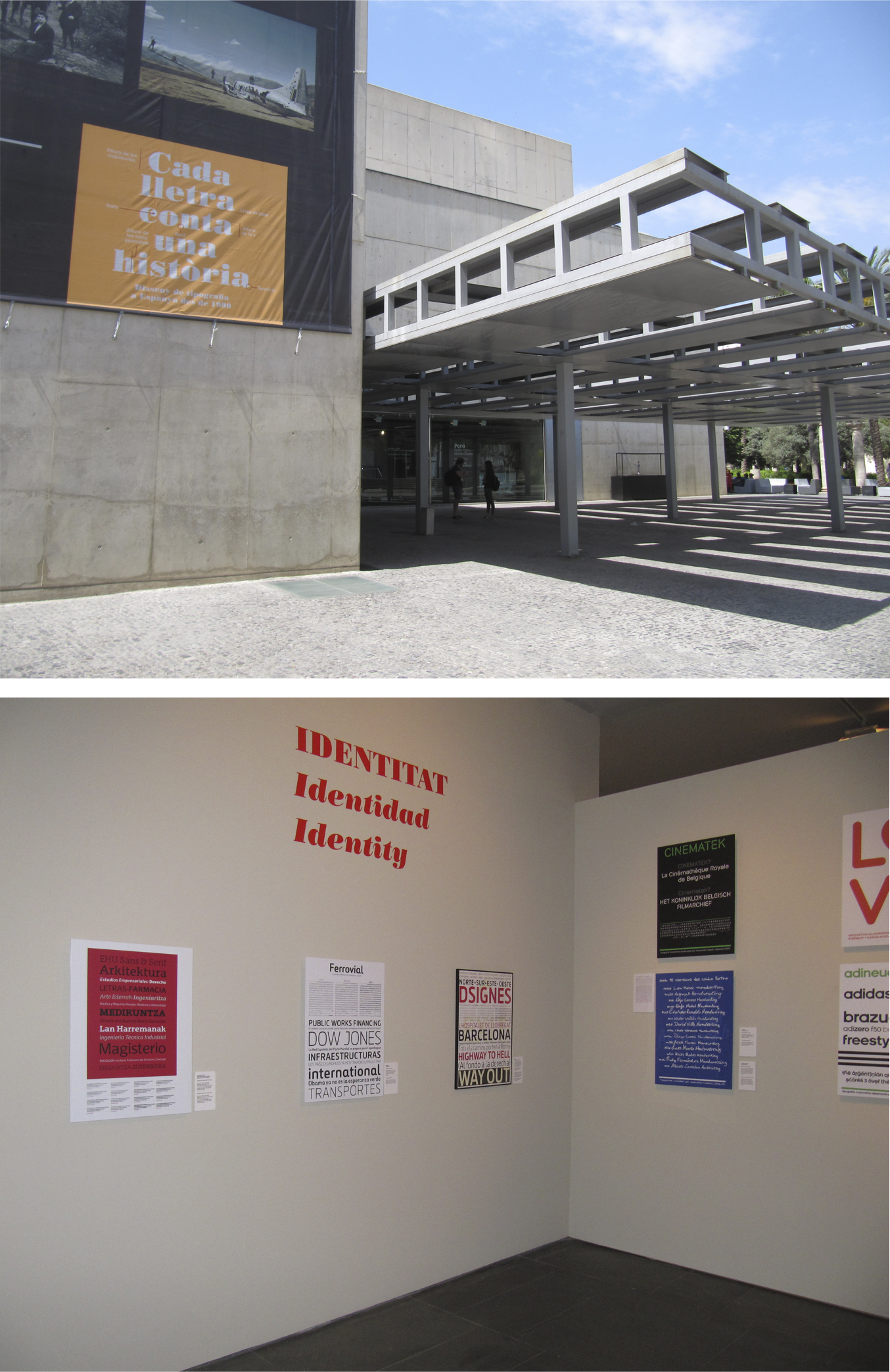
Exposición de caligrafía.
Kaligrafia Arantzazun: idazkera ederraren artea
Caligrafía en Arantzazu: el arte de la bellas escritura
El proyecto «Arantzazu Letraz gunea», fruto de la colaboración entre el Grupo de Investigación en Diseño Gráfico y Tipografía de la UPV/EHU «Letraz», y la Fundación Arantzazu Gaur, ha reunido en Arantzazu a trece de los más renombrados calígrafos del panorama internacional bajo el título Caligrafía en Arantzazu: el arte de la bella escritura. Esta exposición resulta excepcional puesto que se trata de la primera vez que se muestran al público textos en euskera caligrafiados por profesionales:
Ivan Castro
Ewan Clayton
Allan Daastrup
Jota Domínguez
Esther Gordo
Joluvian
Víctor Kams
Oriol Miró
Mr. Zé
Josemaría Passalacqua
Joan Quirós
Esperanza Serrano
Bego Viñuela
Estos calígrafos han manuscrito los poemas de Salbatore Mitxelena Arantzan-zu? (¿Tú en el espino?), Euria (La lluvia) y un fragmento de la canción popular Aldapeko sagarraren (Del manzano de la cuesta), recogidos en el libro Arantzazu: euskal-sinismenaren poema (Arantzazu: poema de fe vasca) de 1949.
En las obras expuestas se evidencia cómo la caligrafía no es solamente un acto de traducción que hace visible el pensamiento del poeta, sino que las formas verbales de los poemas y su significado, convertidas en arte visual mediante el trazo gráfico, se ven complementadas y embellecidas.
Exposición de diseño tipográfico.
Alfabetización científica
En su evolución, el ser humano se ha enfrentado a un sinnúmero de preguntas para desentrañar los misterios de la naturaleza. En el proceso de superación de estos obstáculos ha tenido que recurrir a diferentes estrategias, siempre partiendo desde la curiosidad, la observación y el asombro. Unas cualidades humanas que han permitido acrecentar unos conocimientos que, en gran parte, se han significado y transmitido gracias a las letras. Este conjunto de conocimientos sobre las cosas es la Ciencia.
A través de cincuenta piezas tipográficas esta exposición propone un camino lleno de «preguntas» visuales, que retan a descubrir el contenido de una selección de citas célebres sobre la ciencia. Ideas enunciadas por personalidades científicas, que pretenden hacer reflexionar e identificarse con ellas a quien las lee. Teorías particulares, elaboradas a partir de experiencias personales, que en determinados momentos pueden servir para resolver problemas desde un punto de vista diferente. Fórmulas magistrales que no se aprenden en los libros.
Un recorrido que, a su vez, sugiere una reflexión sobre la esencia misma de la ciencia: suscitar curiosidad, generar preguntas, encontrar las causas de lo que vemos, resolver entresijos y abrir conocimientos. Un paisaje de imágenes de palabras sobre la ciencia que quiere llamar la atención de los ojos de las personas en cosas que, a través de una dimensión estética de las letras, despierte esas estrategias innatas de los individuos y reconduzca el pensamiento —y  quizás la misma «con-ciencia»—, hacia aquellas actitudes y aptitudes humanas que definen, en toda su dimensión, lo que es «Ciencia».
Exposición «Cada lletra conta una historia. Disseny de tipografia a Espanya des de 1990»
La fuente «EHU tipografia» ha sido seleccionada para esta exposición, producida por la Diputació de Valencia, en la que se recoge la creación tipográfica más significativa realizada en el estado español desde 1990. Organizada en diferentes ámbitos, un especimen tipográfico de nuestro proyecto ha sido exhibido en el apartado de «identidad».
Exposición Tipografía EHU
La fuente tipográfica EHU es el resultado de un proyecto de investigación, realizado dentro de la propia Universidad del País Vasco/Euskal Herriko Unibertsitatea, cuyo objetivo ha sido la creación de una tipografía específica que forme parte de la gestión de su identidad visual corporativa.